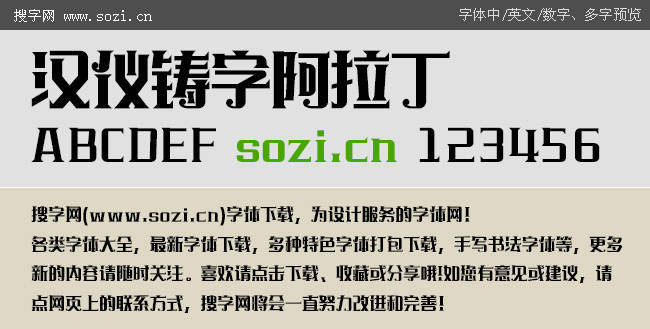
漢儀鑄字阿拉丁
搜字網(wǎng)給大家提供一款漢儀鑄字阿拉丁中文字體下載漢儀鑄字阿拉丁字體筆觸較為粗實,字體清晰大氣,適合應(yīng)用與藝術(shù)設(shè)計、平面宣傳設(shè)計、網(wǎng)頁設(shè)計、海報設(shè)計等應(yīng)用。(本字體為個人非商用版,如需要商用請聯(lián)系漢儀公司購買版權(quán))